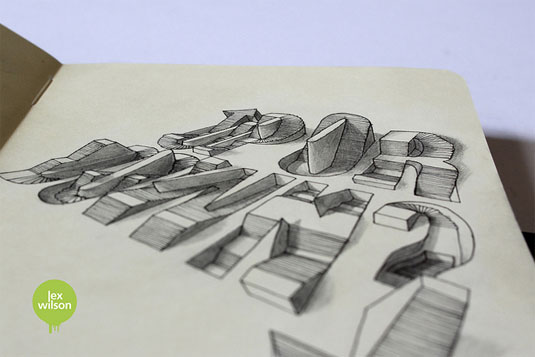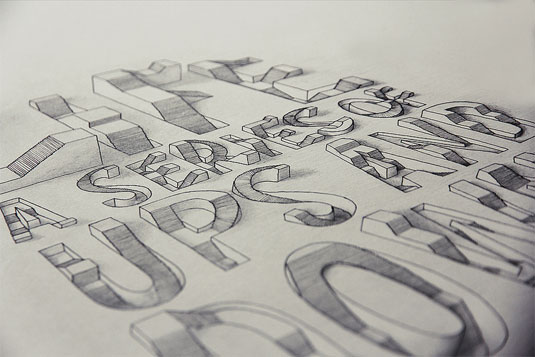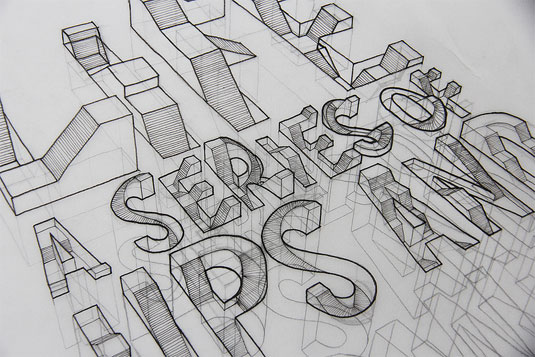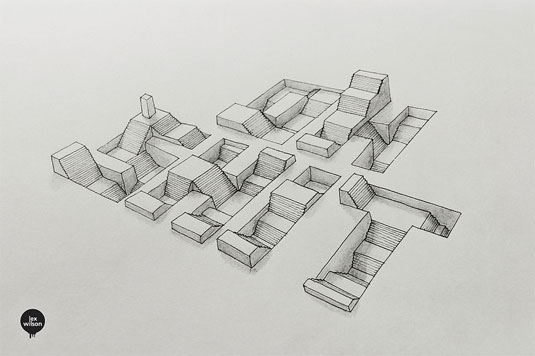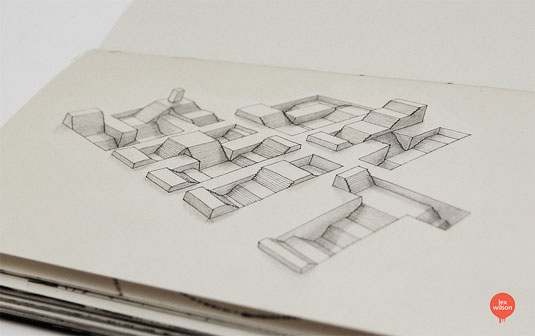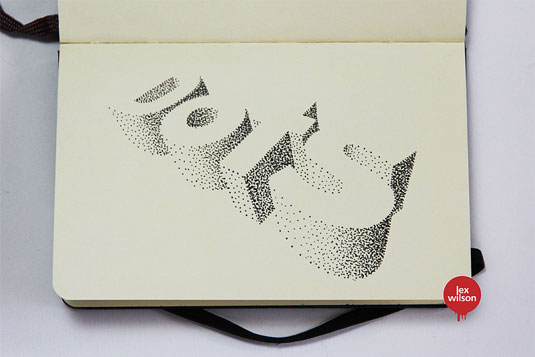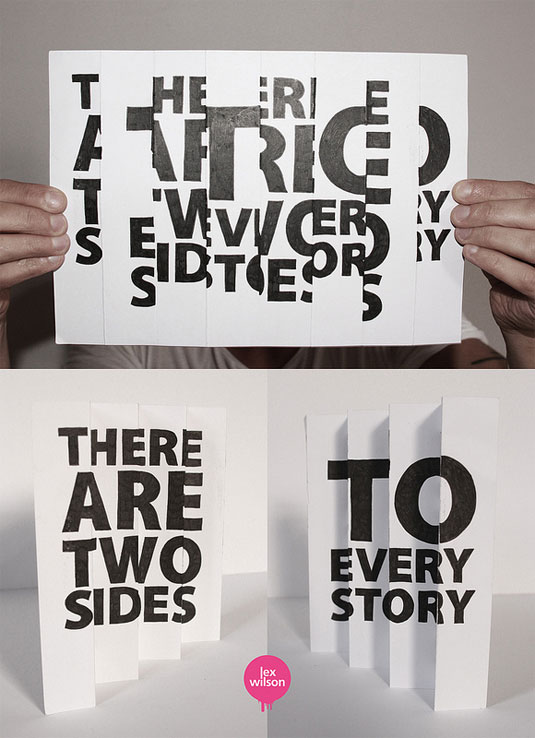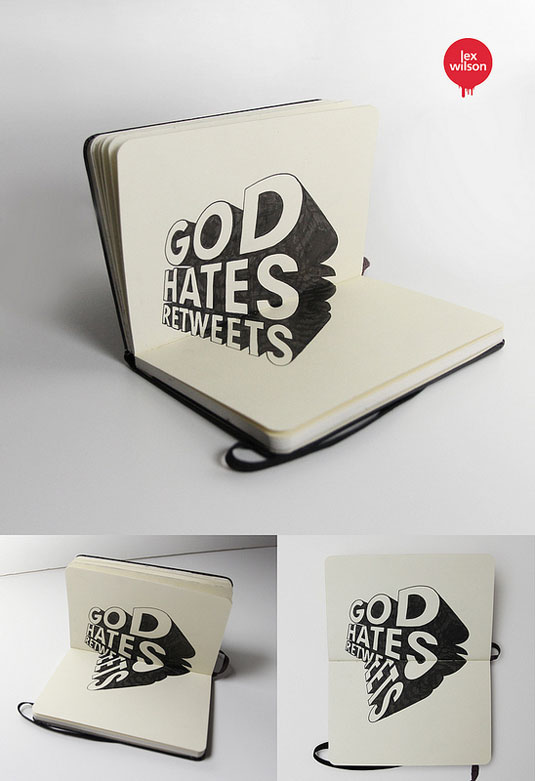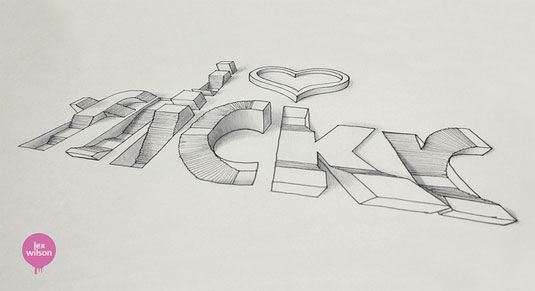
Tipografia com efeitos 3D para te dar um nó na cabeça
Ilustrações fora do normal e 3D de Lex Wilson (6)
É isso mesmo que você viu, o artista Lex Wilson desenvolveu uma nova forma de apresentar seu trabalho de ilustrador, ele criou ilustrações 3D em tipografias em textos simples, não estou falando de tipografia com Bevel Emboss no Photoshop não é uma tipografia totalmente diferente!
É muito mais do que isso, ele desenvolveu uma forma de dar um realismo bem diferente as fontes, ele fez com que as letras estivessem vivas e que fosse reais, com isso ele colocou escadas que sobem e descem, é realmente uma coisa fora do normal!
Além disso ele faz outras brincadeiras com as letras e todos estes desenhos criativos são feitos em um simples caderno Moleskine, por mais que eu fique aqui horas escrevendo eu nunca vou conseguir descrever como é demais o seu trabalho, então veja ai o que vocês acham.
Ilustrações fora do normal e 3D de Lex Wilson (1)
Ilustrações fora do normal e 3D de Lex Wilson (2)
Ilustrações fora do normal e 3D de Lex Wilson (3)
Ilustrações fora do normal e 3D de Lex Wilson (4)
Ilustrações fora do normal e 3D de Lex Wilson (5)
Ilustrações fora do normal e 3D de Lex Wilson (6)
Ilustrações fora do normal e 3D de Lex Wilson (7)
Ilustrações fora do normal e 3D de Lex Wilson (8)
Ilustrações fora do normal e 3D de Lex Wilson (9)